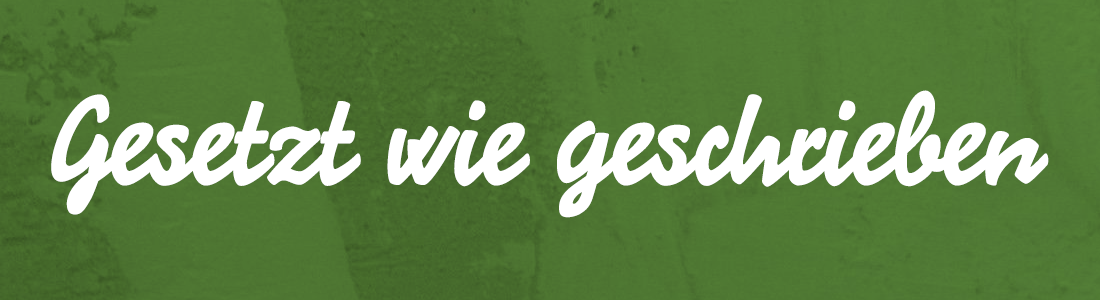
In den 1930er-Jahren waren verbundene Werbeschreibschriften im Trend. Diese Schriften brachten den informellen Charakter handgeschriebener Lettering-Schriftzüge von Schildermalern und Gebrauchsgrafikern in den Bereich der Satzschrift. Den Anfang machten die Schriften Signal (Berthold) und Energos (Schriftguß) in den Jahren 1931 bis 1932. In rascher Folge erschienen bei konkurrierenden Schriftanbietern ähnliche, eher monolineare und verbundene Werbeschreibschriften: Elan (Stempel), Veltro (Nebiolo), Werbeschrift Mammut (Wagner). Im anglo-amerikanischen Raum erfreute sich die Kaufmann (ATF, 1936) großer Beliebtheit.